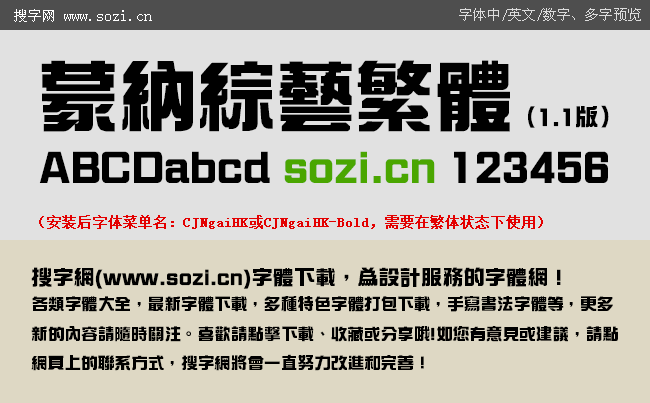
蒙納綜藝繁體
搜字網(wǎng)提供一款蒙納綜藝繁體下載。綜藝體是黑體的一種變體,也是藝術(shù)字的一種。特點(diǎn)是筆劃更粗,盡量將空間充滿。同時(shí)為了美觀,對拐彎處的處理較為圓潤。蒙納綜藝體筆結(jié)構(gòu)美觀,字體厚重。適用于廣告、報(bào)刊等的標(biāo)題及海報(bào)展板等設(shè)計(jì)場合使用。